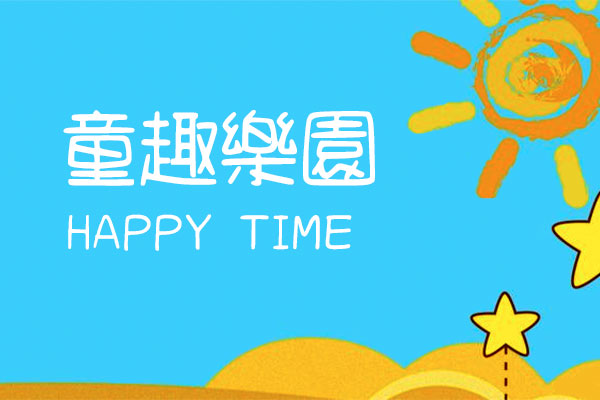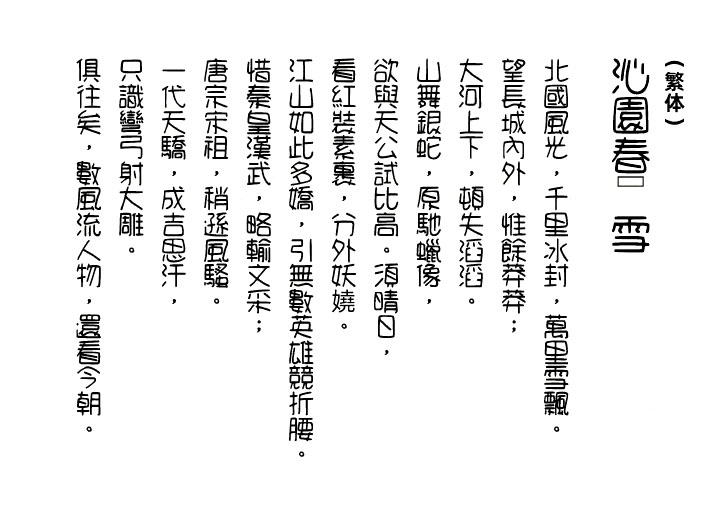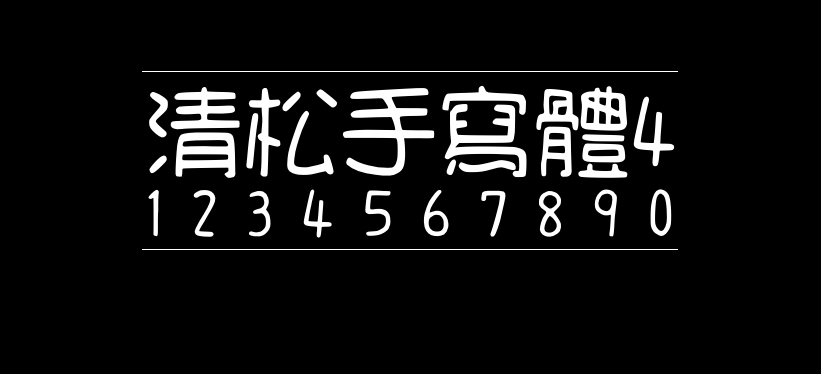
清松手写体4
清松手写体4(JasonHandwriting4)是游清松创作的第四款手写字体。该字体轻松可爱,适合各种轻松、愉悦、童趣的场合。由于台湾省的文字以繁体字为主,所以该字体繁体支持得较好,而简体字会有部分缺字现象。
清松手写体系列是台湾人游清松在稿纸上用原子笔手写,通过「守写字」网站产生出初稿字型档,再通过字型软件后制加工而成的手写字型。